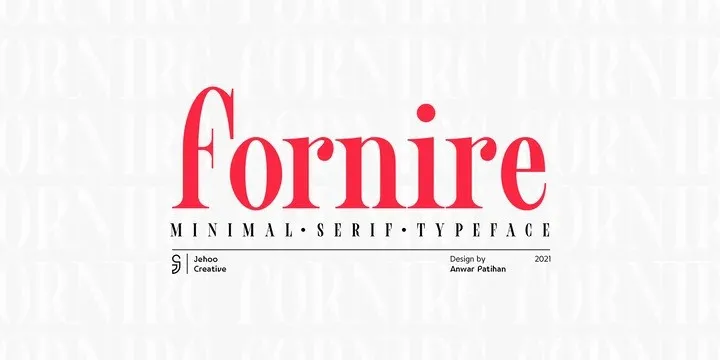
Fornire Font – Download Grátis
A fonte Fornire é uma elegante serif que se destaca pela sua simplicidade minimalista e proporção equilibrada entre letras e espaçamento. Desenvolvida pelo designer Jehoo Creative, a Fornire mantém seus caracteres finos para enfatizar a aparência do tipo. O espaçamento entre os caracteres é mais apertado em relação à média, criando um impacto dramático e marcante. Esta fonte se destaca por seu recurso OpenType que inclui uma alternativa para as letras A, B, E, F, P e R, que são notáveis e facilmente reconhecíveis. Esses detalhes criativos não só a tornam excelente para trabalhos de propaganda como cartazes, capas de revistas ou embalagens, mas também a tornam um recurso versátil para diversas aplicações designográficas. Seja em uma apresentação de poster poderosa ou na elaboração de um design de site, a Fornire é uma escolha confiável que complementará sua criação com estilo e elegância.